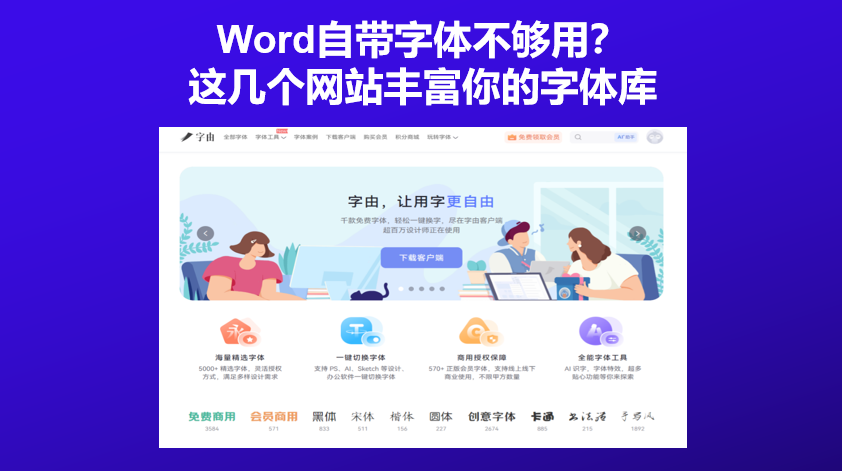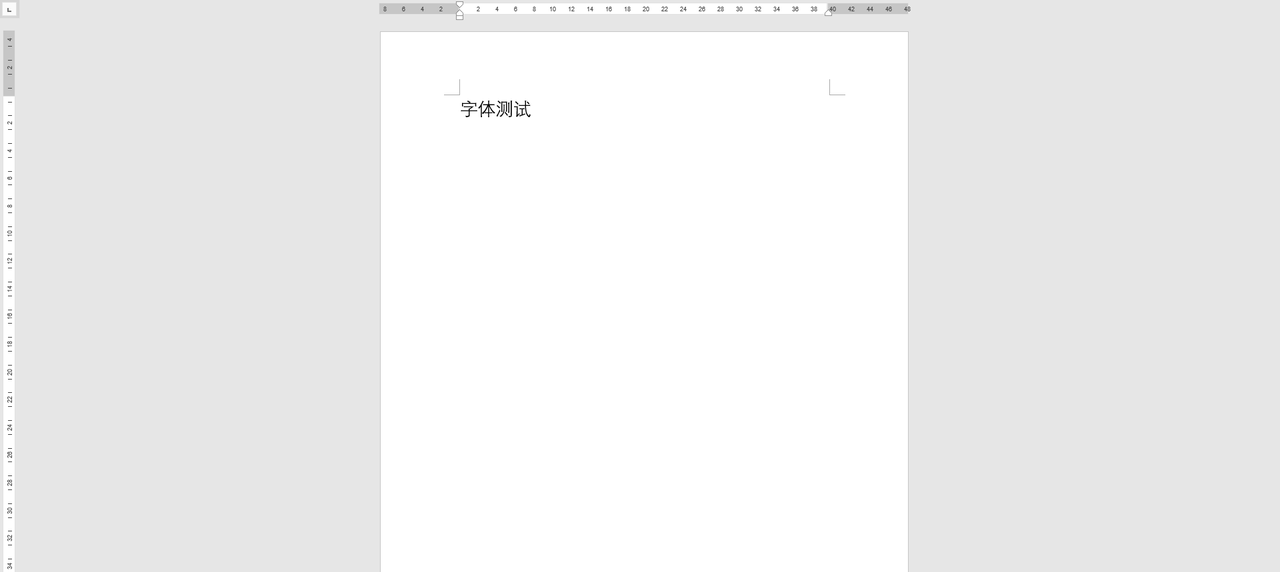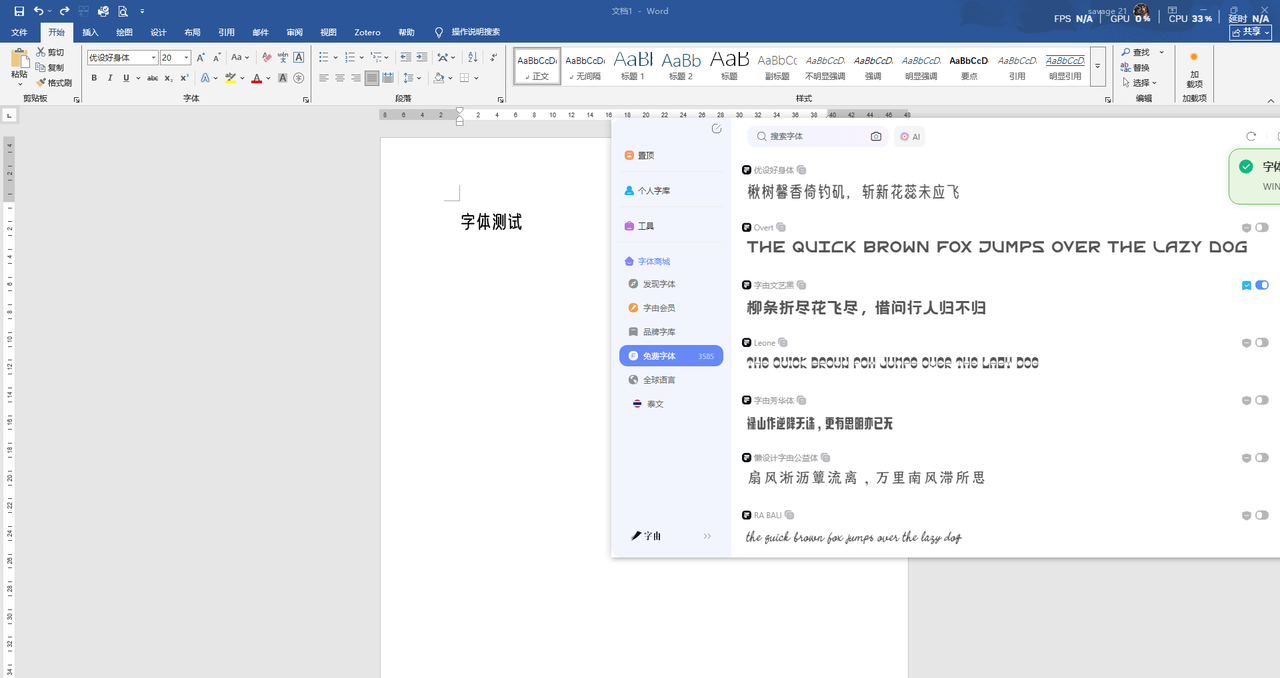
Word自带字体不够用?这几个网站丰富你的字体库
在用word字体文档的时候,你肯定会因为自带的系统字体太少而头疼,现在没有好用的字体库确实是不太行,做报告想用个好看的手写体,没有;做简历想用个优雅的衬线体,也没有;做海报想用个酷炫的艺术字,更没有。但是实际上word字体库是可以扩充的,并不是只能用那几个。只要把新字体装进电脑,Word里就能用。但问题是:去哪找?怎么装?那么今天我就把私藏的4 个Word字体资源网站分享出来,需要的可以收藏!
今天要介绍的第一款字体网站是字由,它非常适合普通办公族。你在Word里做文档时觉得word字体不够用,打开字由客户端,选一款字体,点一下,Word里的文字就换好了。不需要下载字体文件,不需要解压安装,不需要重启Word。这才是真正的“一键添加word字体”。
首先我会介绍一些有哪些好用的字体。字由收录了超过10500 款字体,其中3585 款是免费可商用的。你日常需要的Word字体,基本都能在这里找到:
- 正文排版:推荐“思源黑体 Medium”“优设好身体”。前者是经典开源字体,清晰易读;后者字形方正饱满,长时间看文档不累眼。
- 标题设计:推荐“字由文艺黑”“优设标题黑”。前者稳重带一点手写感,适合报告大标题;后者方正有力,适合PPT封面。
- 手写风格:推荐“字由芳华体”“沐瑶软笔手写”。前者温柔手写,适合邀请函、贺卡;后者圆润治愈.
- 国风书法:推荐“江西拙楷”“北窗墨刃”。前者朴拙手工感,适合传统文化主题。
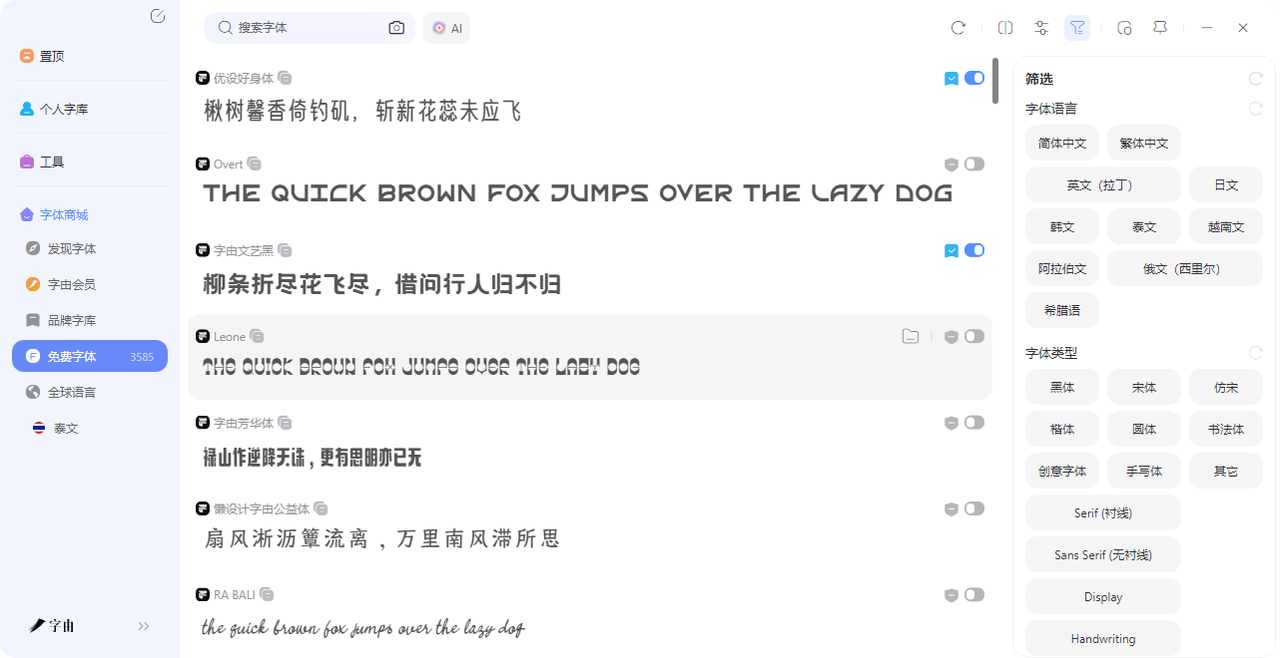
2、JustFreeFonts
如果你不介意传统安装方式,这个网站是很好的word字体资源库。JustFreeFonts收录了6000多款免费字体,全部适合商用。首页有热门搜索推荐,比如“Signature”“Playful”“Wedding”“Cursive Script”,方便快速定位。它的首页展示了多款精选字体:
- Disolve、Lolly Goals、GRUMMAZ、Puppies Play、Inter Typeface、MomScript
- Latina Popular(手写体)、Firjar(24种字重)、Erben Gothic(展示字体)
每款字体都标注了设计师和风格(Handwritten、Display、Sans Serif),还有“Latest Free Fonts”板块,展示最新上架的免费字体。下载后需要手动安装到电脑,才能在Word里使用。
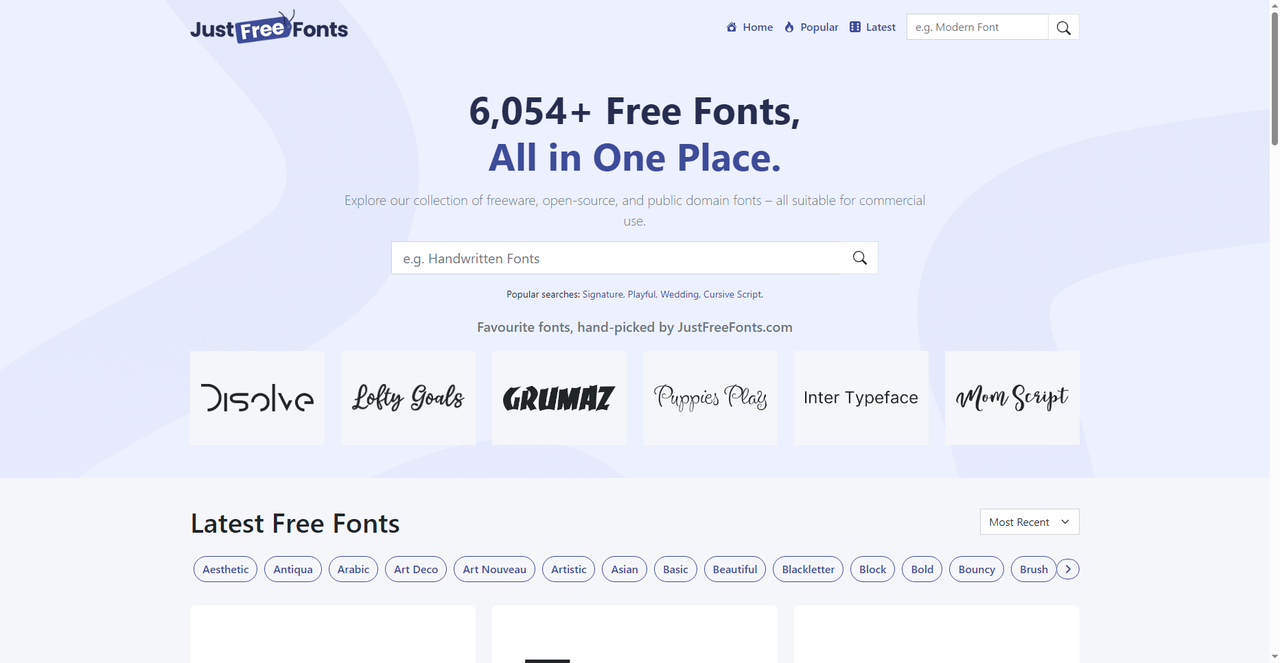
3、FontZone
FontZone是一个运营多年的老牌字体网站,首页写着“Discover 55,000+ Free Fonts”——超过5.7万款免费字体。它的分类很细,右侧有大量风格标签:script、cursive、bold、graffiti、gothic、calligraphy、tattoo、old english、signature、handwriting、handwritten、serif、bubble、sport、vintage、sans serif……每款字体都有预览,输入文字就能看效果。下载后需要手动安装到电脑。它的优势是体量巨大,几乎能找到任何你想要的风格。缺点是筛选起来需要花点时间,而且很多字体标注了“Personal Use Free”,商用需要仔细查看授权
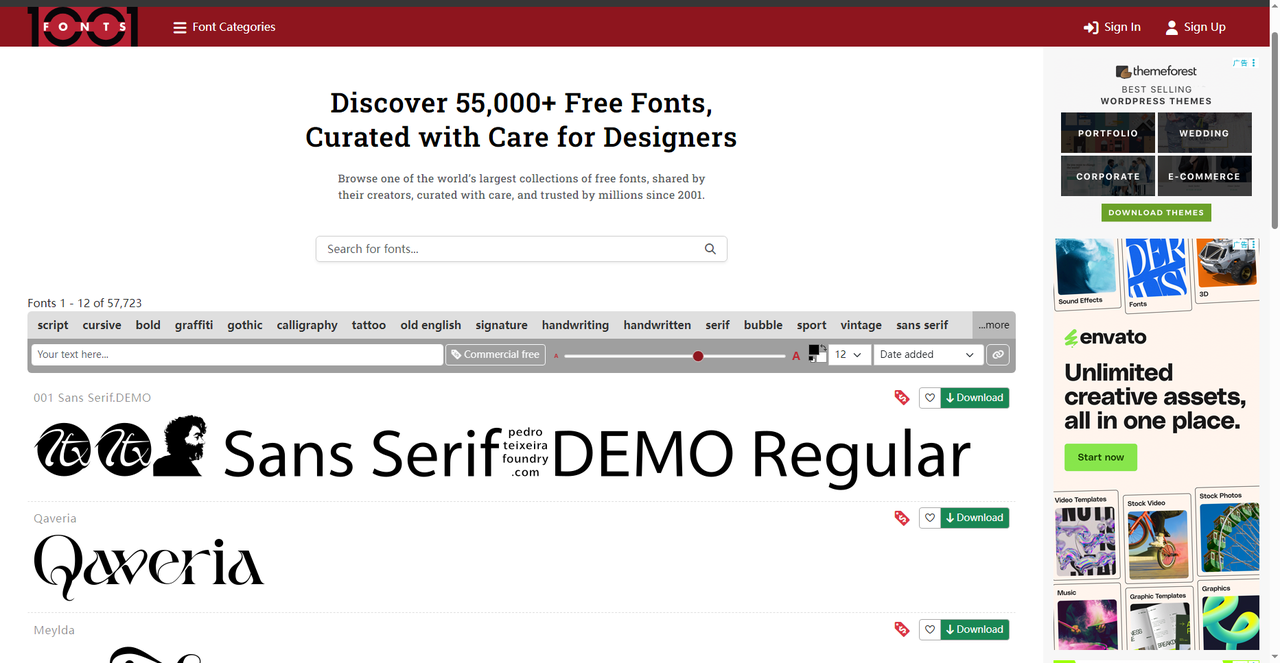
4、DaFont
DaFont是我最早知道的免费字体网站,运营了二十多年。它的分类非常传统但实用:Fancy、Fire Ice、Foreign look、Techno、Gothic、Basic、Script、Dingbats……每个大类下面还有细分,比如Fancy下面有Cartoon、Comic、Groovy、Old School、Western、Eroded、Distorted、Horror。首页会展示最新上传的字体,比如“Super Starfish”(100% Free)、“Nicholas”(Free for personal use)、“Johnstone Airline”(Donationware)。每款字体都有详细的安装说明和授权标注。DaFont的字体多为个人免费使用,商用需要仔细看授权或购买。
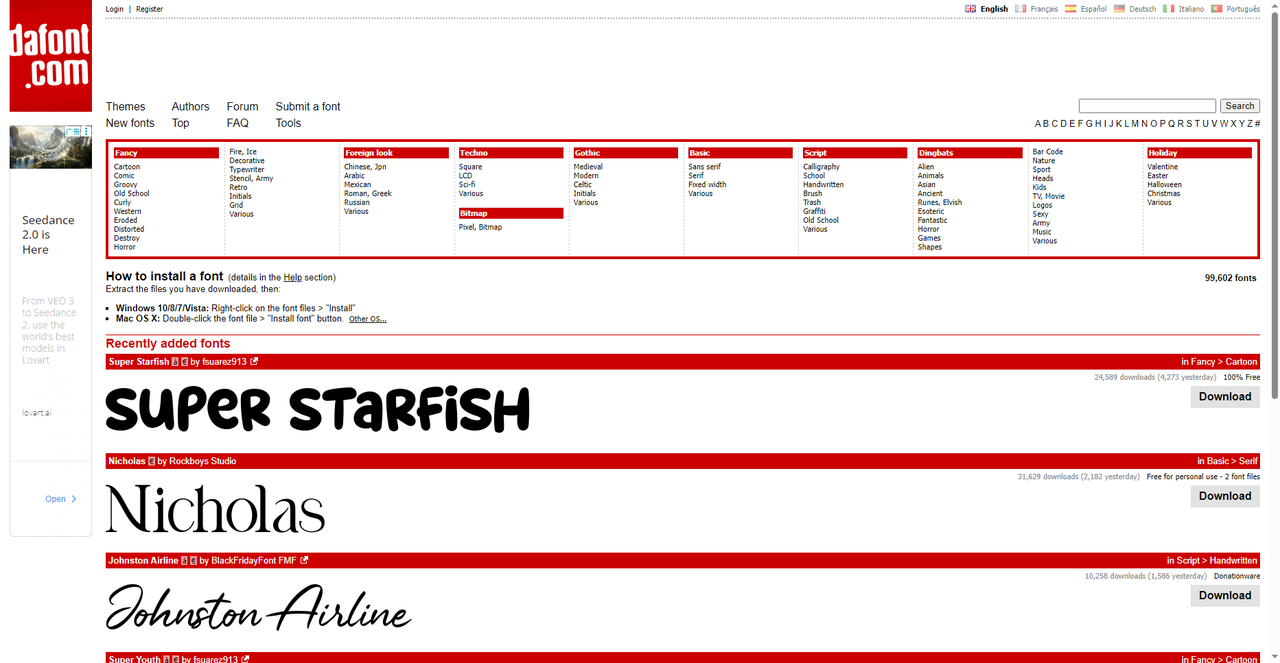
5、Free Fonts & Popular Fonts
最后一个网站展示了2026年的热门免费字体,比如“Alteix Sans”“Stencil PTx Sprayed”“Ayaha”等。每款字体都有下载次数(比如40445 downloads),可以帮你判断受欢迎程度。它还提供了“Commercial-use”和“Personal Use Free”两种筛选,方便你按授权类型选择。
以上就是今天要介绍的这几个word字体网站,每个都非常好用,JustFreeFonts 精选推荐,FontZone 体量巨大,DaFont 分类最全,热门站能看到流行趋势。但它们都有一个共同点:下载后需要手动安装到电脑,才能在Word里使用。而字由不一样。它不需要下载安装,打开客户端,在Word里选中文字,点一下字体,就换好了。如果你经常在Word里做文档、做报告、做简历,字由能帮你省下大量时间。而且它有3585 款免费商用字体,日常用完全够。如果你也觉得Word自带字体不够用,不妨从字由开始试试。下载客户端,打开Word,点一下,新Word字体就有了。